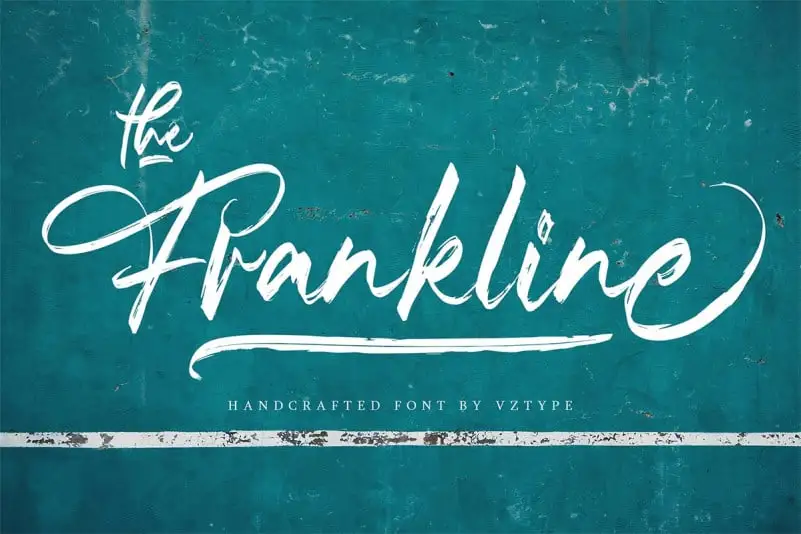
The Frankline Brush Font – Download Grátis
A The Frankline Brush Font é uma seleção excepcional para aqueles que buscam uma fonte agradável e versátil que se destaca na cena dos materiais digitais. Naturalmente fluida, essa fonte brush captura o espírito de um gosto clássico e vintage enquanto oferece um toque moderno em sua tipografia fun e elegante. Suas características inclusas como alternâncias estilizadas permitem uma grande liberdade criativa, desde a criação de logotipos inspiradores até o design de cartões de votos ou materiais publicitários. O suporte internacional para diversas línguas ocidentais incluído garante que The Frankline Brush Font seja capaz de se adaptar e se encaixar em uma variedade de projetos, desde banners de logotipo até adesivos de t-shirt ou selos de eventos. Essa font é ideal para designers gráficos buscando dar um toque especial a seus trabalhos, com suas opções estilizadas permitindo diferentes efeitos visuais que podem se adaptar às várias necessidades de projeto.